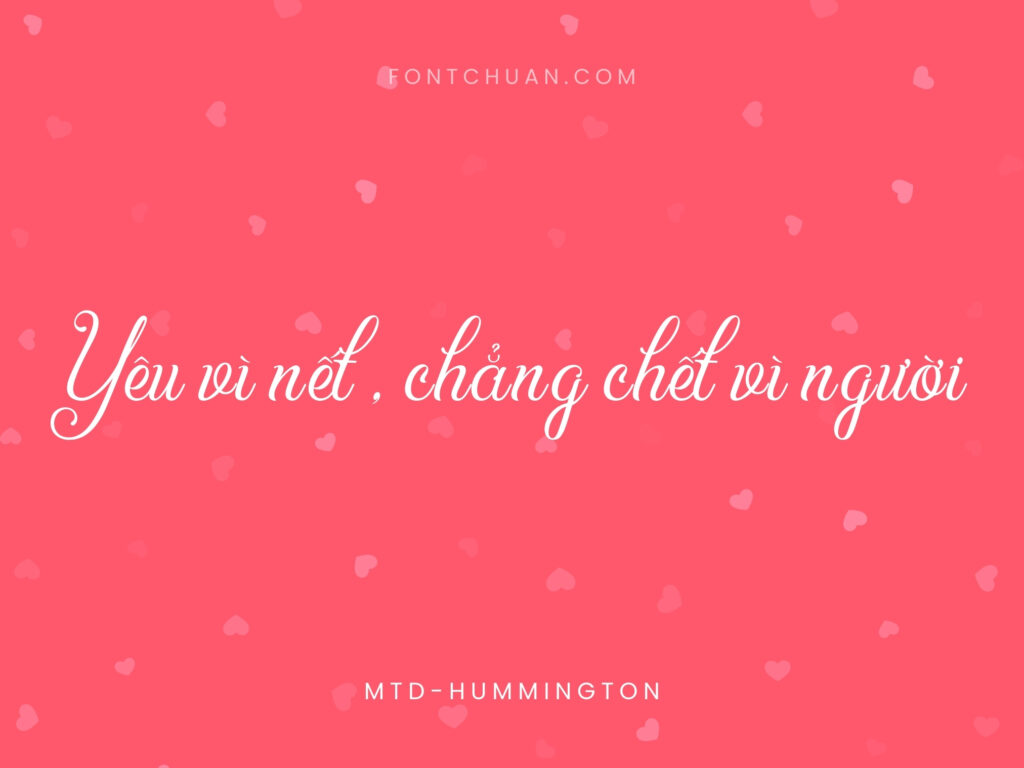
Font MTD Hummington Việt Hóa
Tác giả Font: Zeune Type Foundry
Font MTD Hummington là một phông chữ script mang phong cách cổ điển, được thiết kế bởi Zeune Type Foundry và đã được Việt hóa bởi Mộc Hạ. Font này hỗ trợ đầy đủ tiếng Việt cùng hơn 90 ngôn ngữ khác, giúp mở rộng khả năng ứng dụng trong các thiết kế đa ngôn ngữ. Đây là một trong những phông chữ được cộng đồng thiết kế đánh giá cao và sử dụng trong nhiều dự án sáng tạo, đáp ứng nhu cầu đa dạng của người dùng.
MTD Hummington nổi bật với các đường nét mềm mại và uyển chuyển, mang đến cảm giác thanh lịch và sang trọng. Font rất phù hợp cho các thiết kế logo, tiêu đề, bao bì sản phẩm, thiệp mời và các ấn phẩm đòi hỏi sự tinh tế và nghệ thuật. Các ngành nghề phù hợp bao gồm quảng cáo, giáo dục, công nghệ, thiệp cưới và ảnh cưới. Font này cũng lý tưởng cho các sự kiện như Tết, Giáng sinh, Valentine và các lễ hội khác.